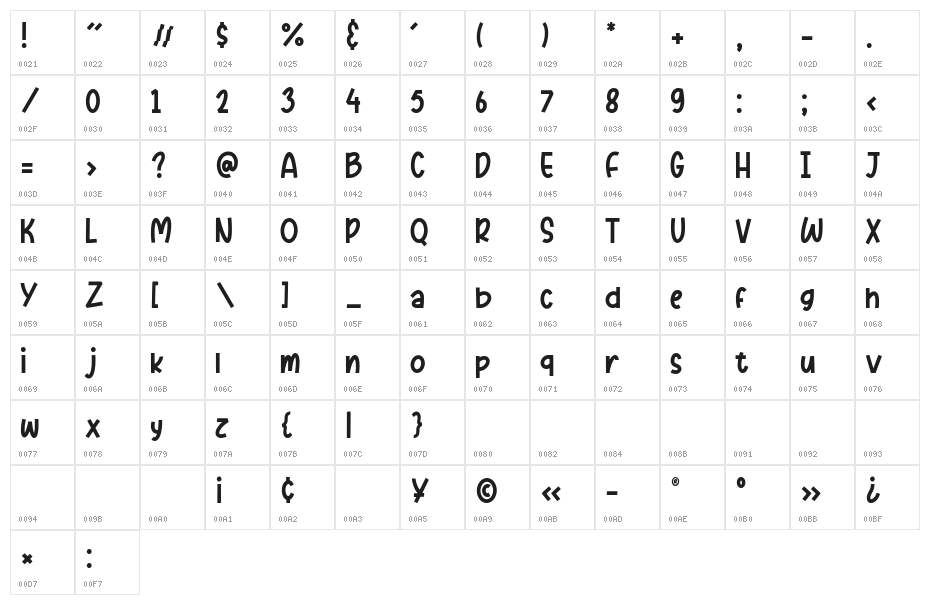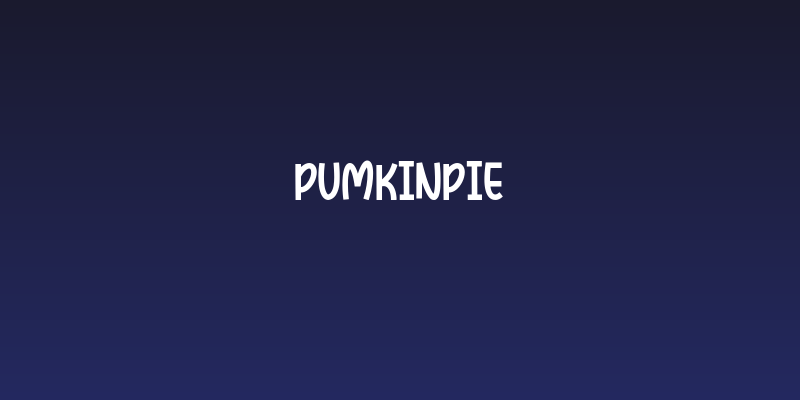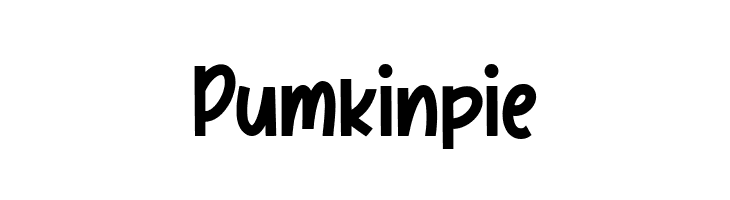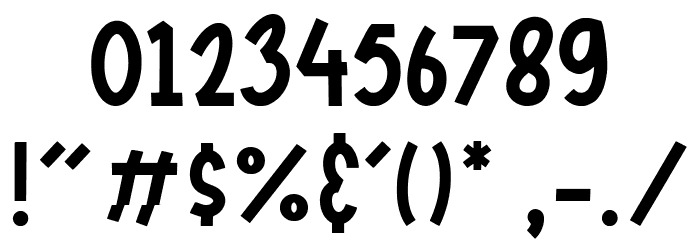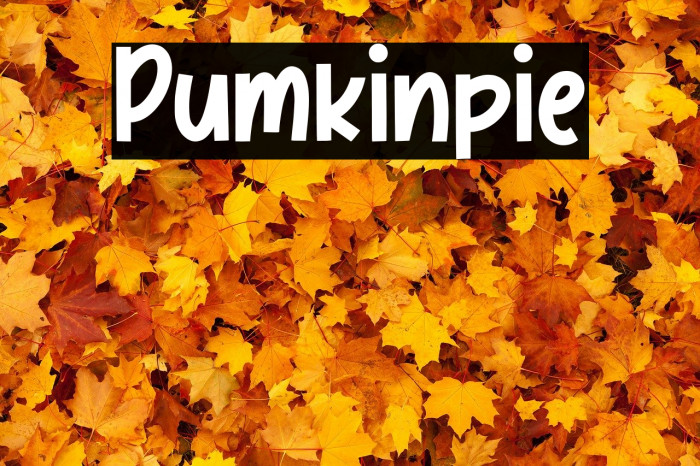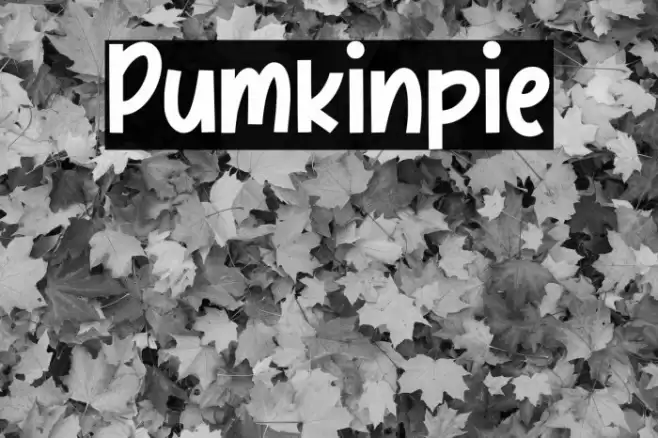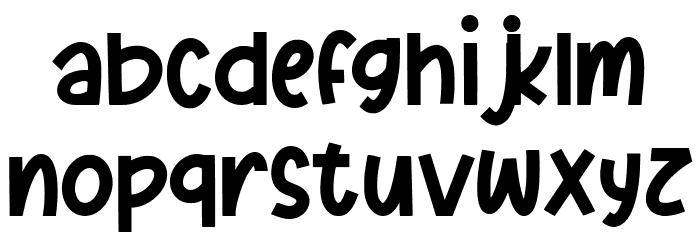
Pumkinpie Font
Fonts by Balpirick Studio
| Gesamtstil | Playful |
| Vorgeschlagene Projekte | Perfect for children's books, playful branding, party invitations, and casual social media graphics. |